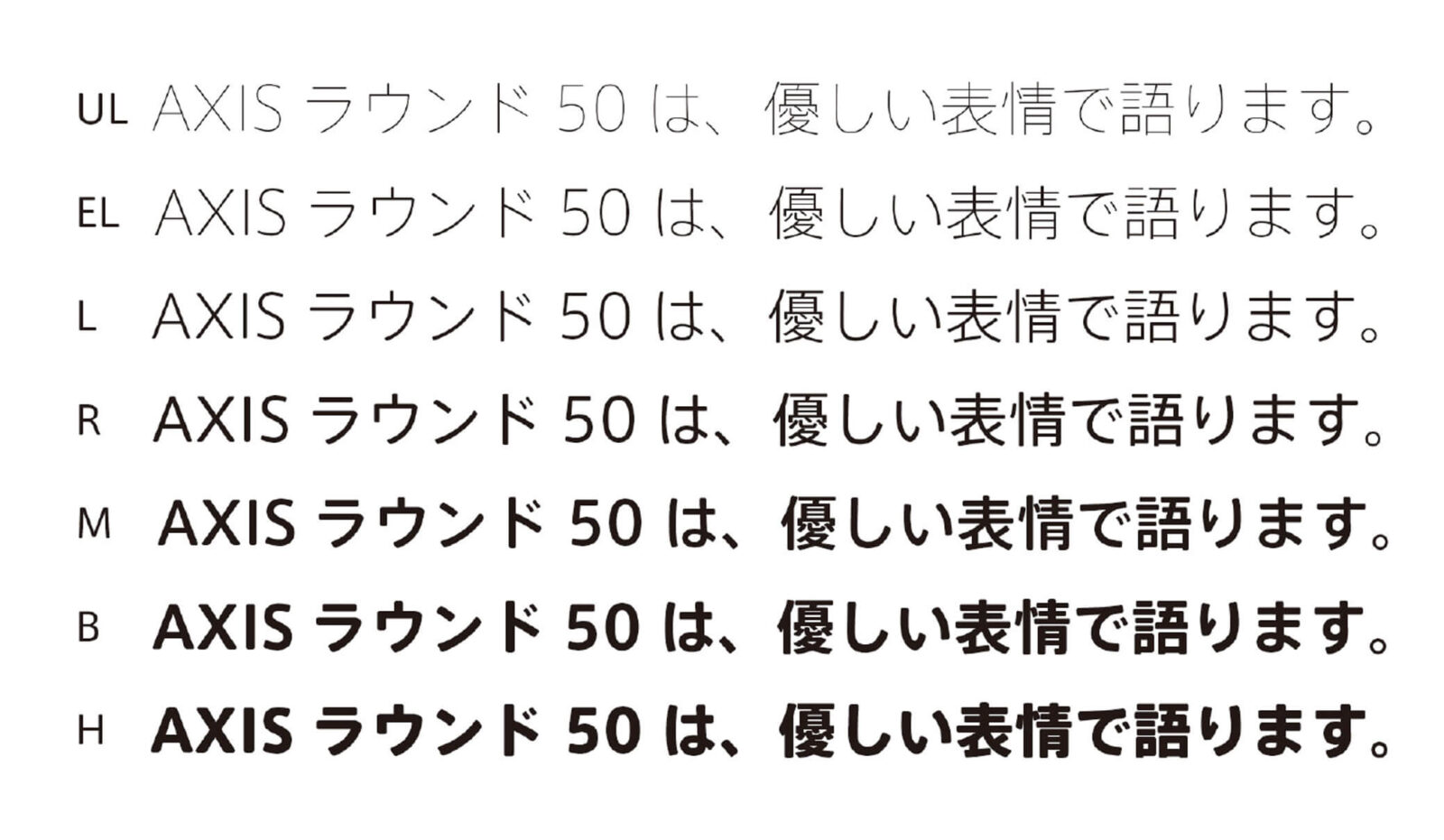
タイププロジェクト、AXIS Font ファミリーの新シリーズ 「AXIS ラウンド 50」を発表
AXIS Font の基本設計はそのままに、サンセリフ体の角を丸めたラウンド系フォント
タイププロジェクト株式会社 (東京都練馬区 代表取締役社長 鈴木 功、以下 タイププロジェクト) は、より豊かな表現を実現する新書体「AXIS ラウンド 50」を発表しました。AXIS ラウンド 50は、AXIS Fontの特徴であるシンプルで明快なデザインを受け継ぎ、サンセリフ体のシャープな輪郭にわずかな丸み与えることで、より親しみやすい表現を可能にしました。AXIS ラウンド 50 は、本日より発売を開始いたします。
AXIS Font は、そのすっきりとした印象から、建築やプロダクトの分野で多く導入されています。AXISラウンド 50は、食品や衣料品などの素材の柔らかさを表現したいというユーザーの要望の応え、表現の幅をさらに広げることを目指しています。ウエイトは、UL (ウルトラライト)、EL (エクストラライト)、L(ライト)、R (レギュラー)、M (ミディアム)、B (ボールド)、H (ヘビー)の7種類で、それぞれAXIS Fontベーシックの各ウエイトに対応しています。
AXIS ラウンド 50は、AXIS Fontのストロークの先端の半分を直径とする正円を使って角を丸めたところから命名しています。このパーセンテージは、へビーとボールドに適用していますが、視覚調整によりミディアムとレギュラーは 55%、ライトとエクストラライト、ウルトラライトは60%と、ウエイトごとに丸みの比率を調整しています。また、文字によって、正円ではなく楕円にするなど、安定感を出す処理を施しています。
AXIS ラウンド 50
タイププロジェクトの代表取締役 鈴木 功は、「AXIS ラウンド 50は、AXIS Fontのデビューから15年、AXIS Fontコンプレスのリリースから実に7年ぶりの新シリーズとなります。AXIS ラウンドを開発した最大の理由は、ニュートラルな書体の性質からさまざまな分野で利用されていた AXIS Font にも苦手な場面があることを感じていたからにほかなりません。AXIS Fontが生長しようとしている方向を見きわめ、書体が枝葉を伸ばす手助けをしたともいえます。ユーザーの皆さんによるAXIS Font とAXIS ラウンド 50の使い分けを、楽しみにしています」と述べています。